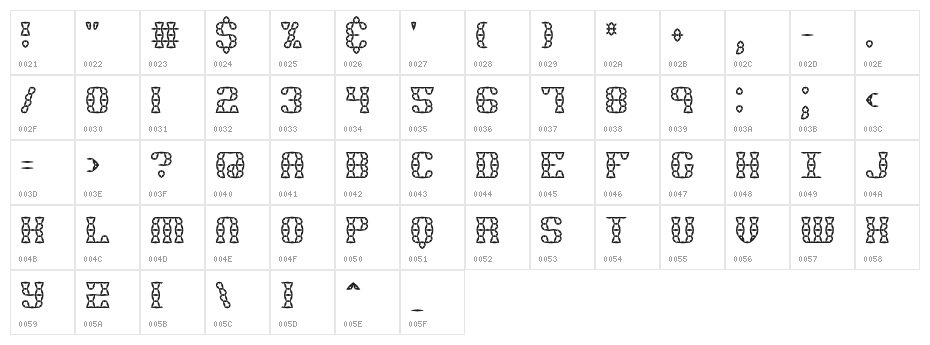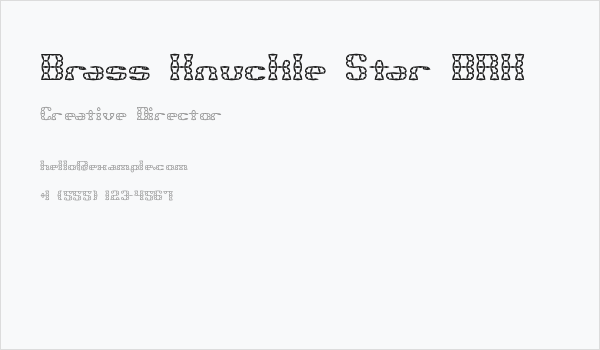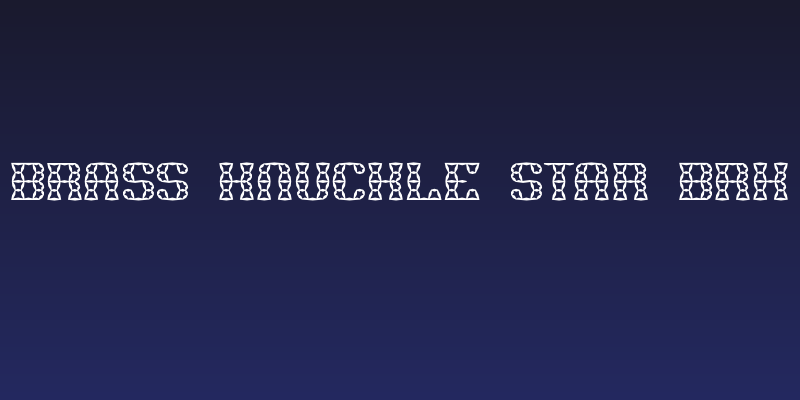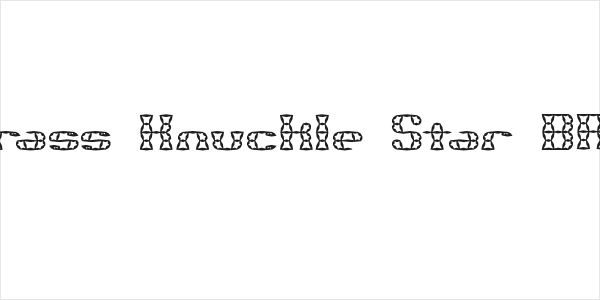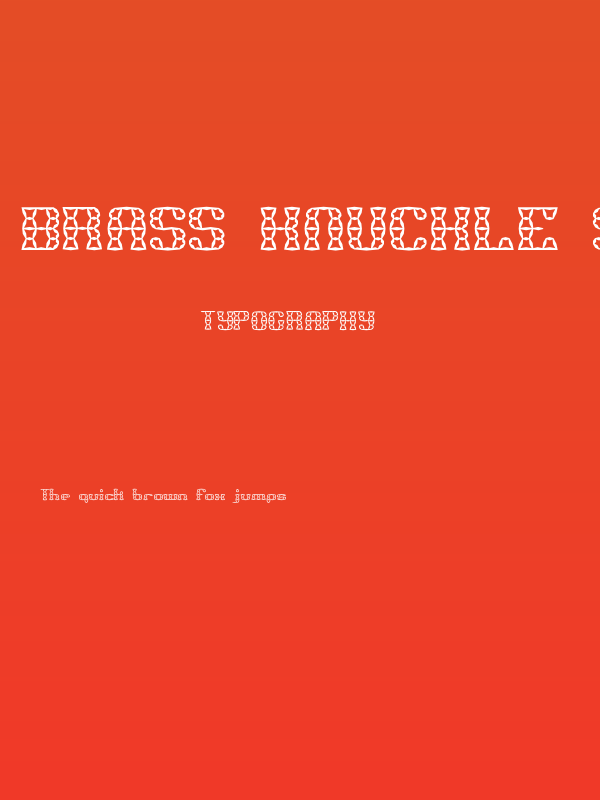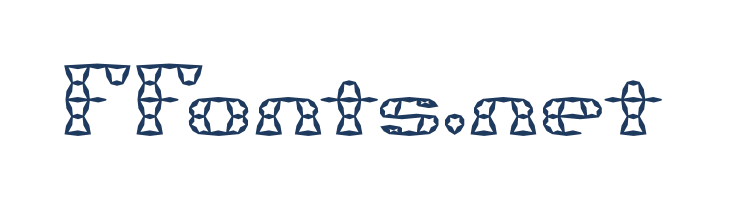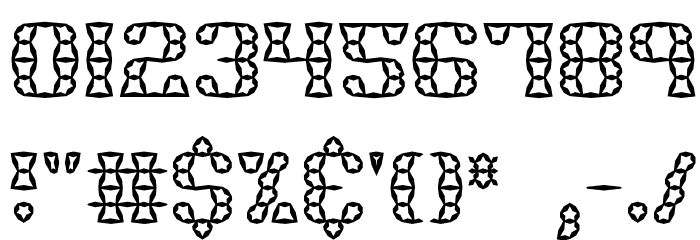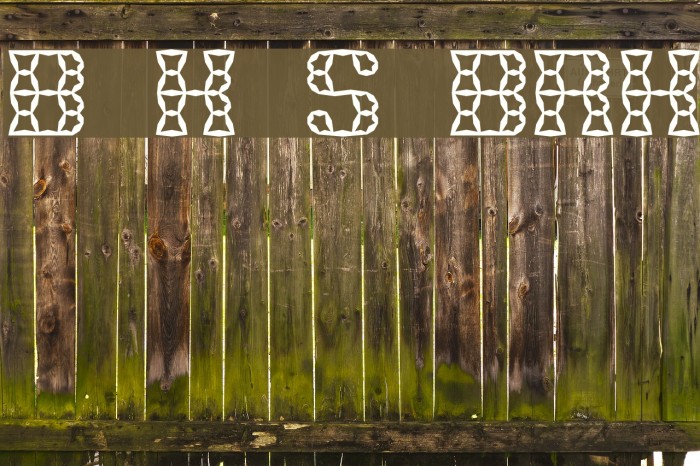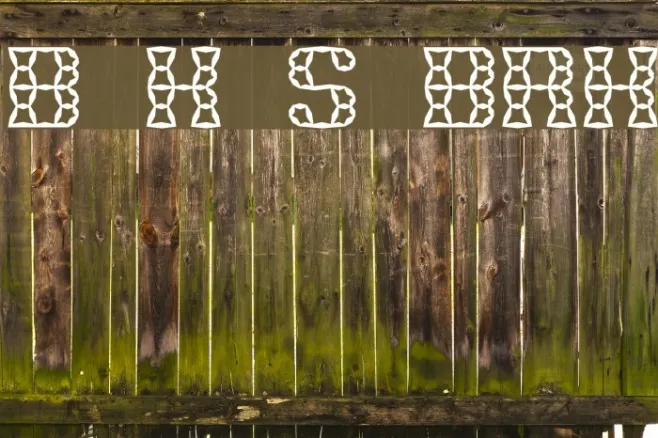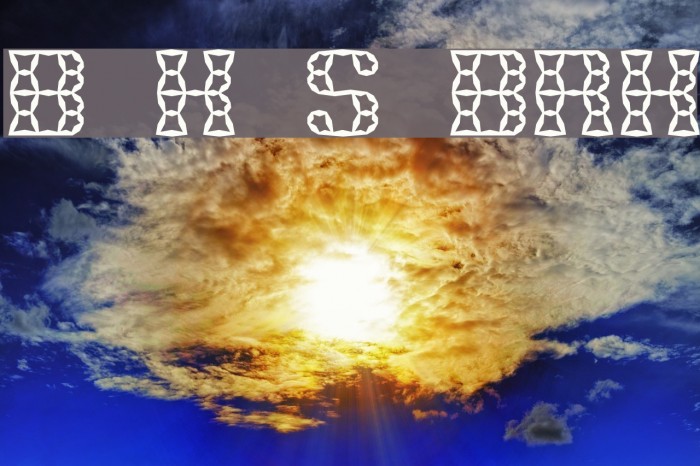
Brass Knuckle Star BRK Font
✎ Outline
| Vorgeschlagene Projekte | Perfect for posters, album covers, branding for edgy or industrial-themed products, and any project needing a strong visual statement. |